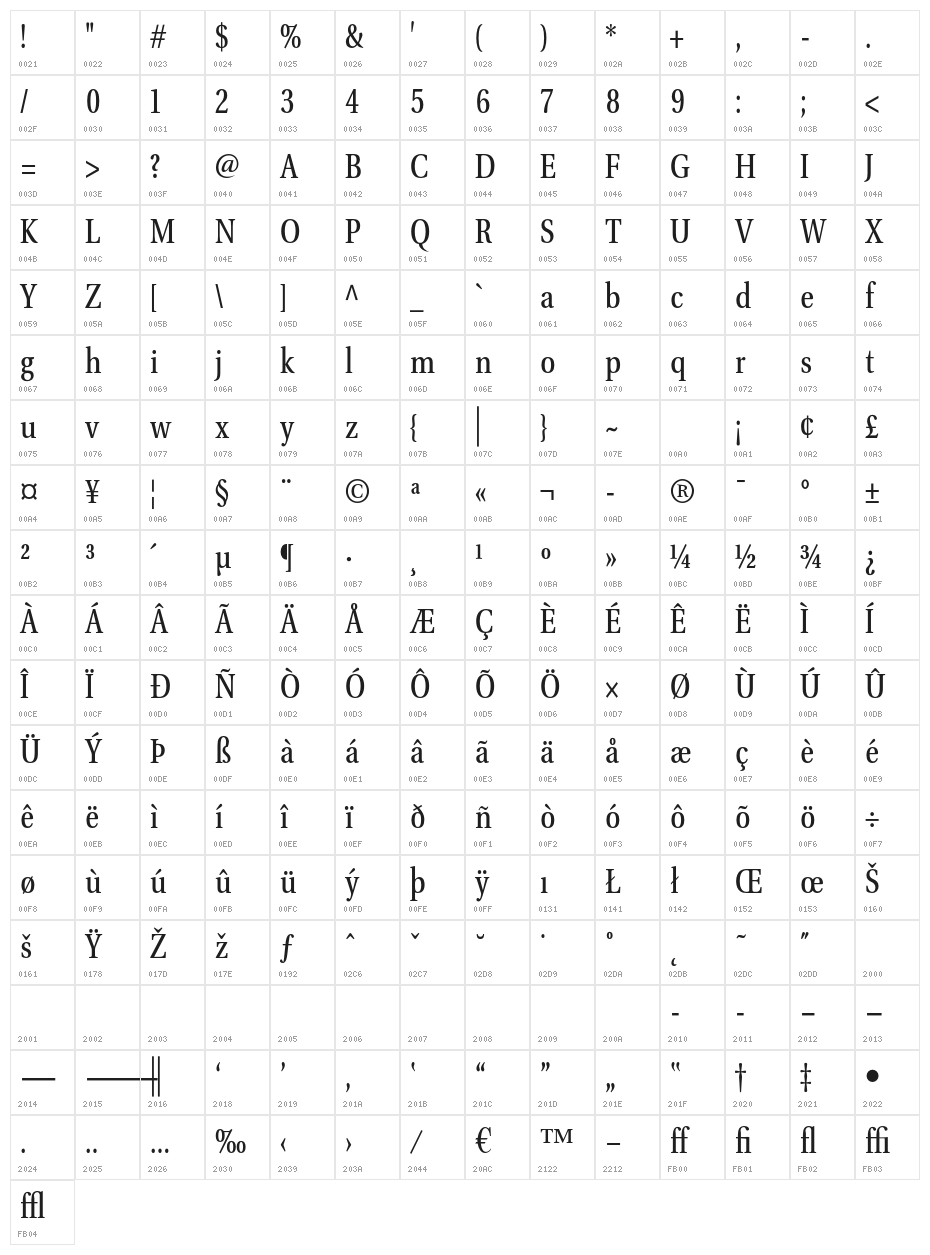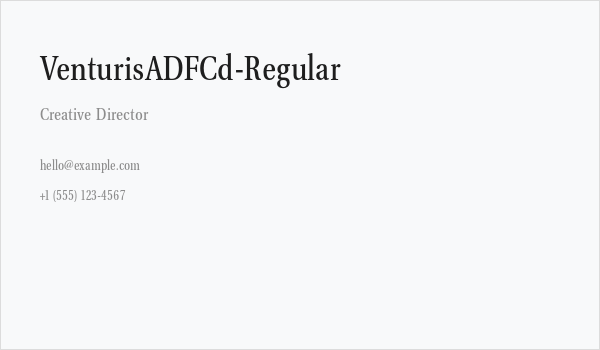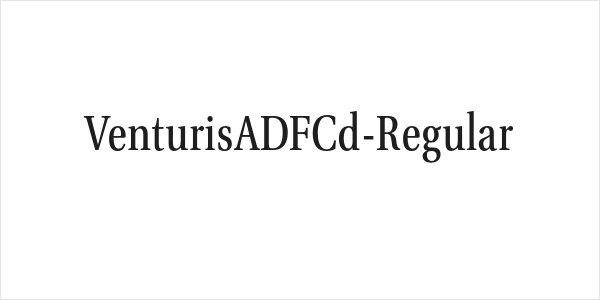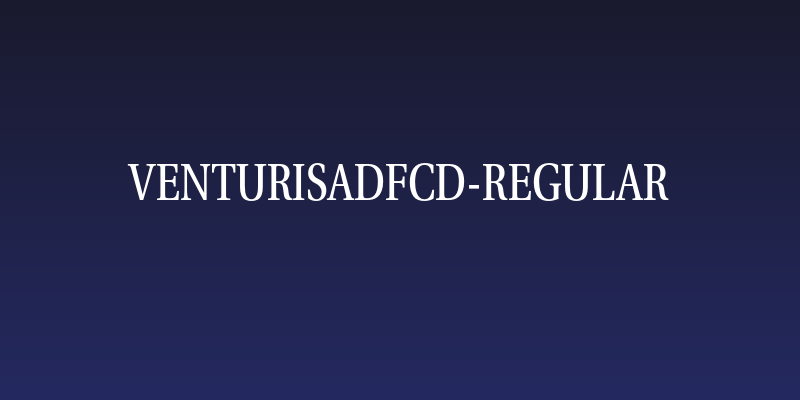
VenturisADFCd-Regular Font
| 分类 | Serif |
| 整体风格 | Classic |
| 使用场景 | Headlines, Body text, Logos |
| 推荐项目 | Ideal for editorial design, formal documents, branding, and any project requiring a sophisticated touch. |